石井中ゴシック
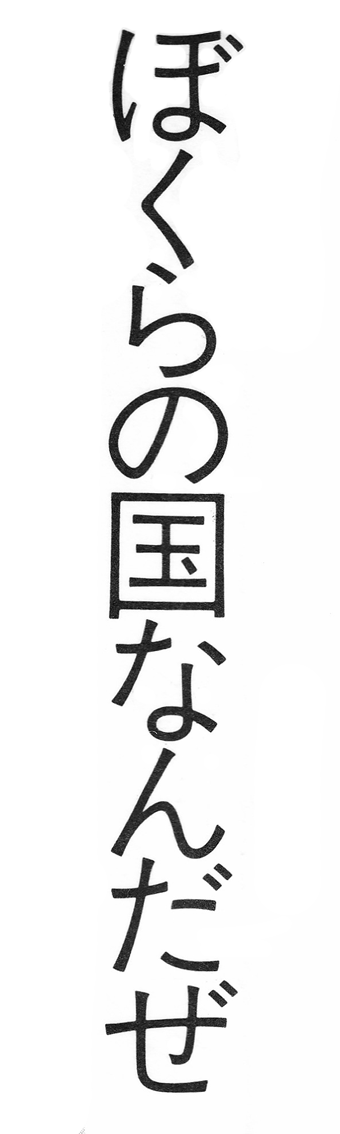
ポケットの なかには ビスケットが ひとつ
ポケットを たたくと ビスケットは ふたつ
もひとつ たたくと ビスケットは みっつ
たたいてみるたび ビスケットは ふえる
そんな ふしぎな ポケットが ほしい
(まどみちお『ふしぎなポケット』)
〈石井中ゴシック〉はあの歌に似ている。
いったいどこが似ているのか、どうしてそんなふうに感じるのか、わざわざ考えてみたことがなかったが、この書体の名前を知る以前からはっきりとそう思っていたし、だから私にとっては、比喩でもなんでもなく、ほんとうに「ビスケットの文字」だった。
高級というわけじゃないけれど、心惹かれる洒落たパッケージ、きっちりと整列している堅実な様。よけいな甘みをくわえていない、保存食みたいなビスケット。
もしも私に絶対音感があったなら、それを音楽で証明してみせるだろう、と考えることがある。
雨だれの音や、ごはん茶碗を並べる音でオーケストラをやってのける名指揮者のように、文字から伝わってくるイメージをうつくしい音にして、みんなに聴かせてあげられるのに、と。
でも残念ながら、私にはそんな音楽的才能はない。鼻歌をうたうのも、音楽をきくのも好きだけど、とにかく習い事全般を疎かにする子どもだったので、五年も習ったピアノは結局、バイエルさえものにならなかった(どうでもいいことだが、ピアノ教室へ行く途中の野原でへびいちごを摘むのが唯一の楽しみだったのを思いだした。田舎だなあ。)
だから私にできるのは、歌を口ずさみながらポケットをたたくことくらいだ。
これがリズムというものだと、いちばん最初に教えられた記憶。
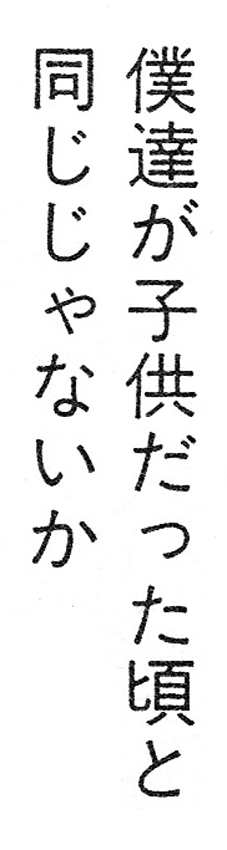
ポケットをたたくたびにビスケットの数が増えるのは、ポケットのなかでビスケットが割れるからだ、と人に聞いたことがある。
(この解釈には諸説あるようだけれど)そのとき私は、へえなるほど、といたく感心し、そういう意味で、この歌はやっぱり〈石井中ゴシック〉に似ていると思った。
この文字でかかれた言葉が目に入ってくるときの感覚は、ビスケットの歯ごたえにそっくりだ。ビスケットが割れる一瞬にくわわる力の、弱くもなく、強くもない、ほんのちょっと、手先に意識が集中する感じ。
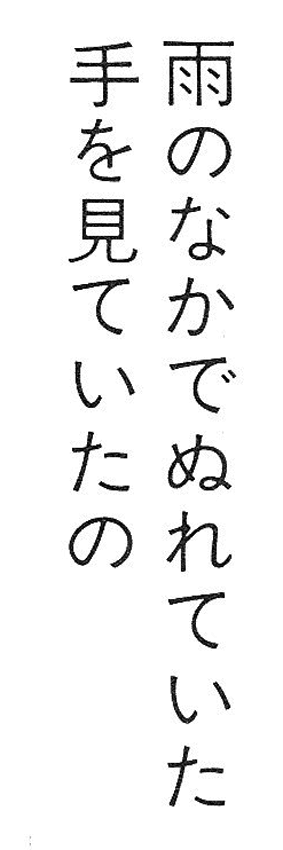
〈石井中ゴシック〉には、だから散文がよく似合う。
中学や高校のころ聴いていたCDの歌詞カードが〈石井中ゴシック〉でかかれているのをみると思わずぐっときてしまうのも、おそらく同じ気分によるものだろう。
それで思いあたることは他にもあって、たとえば、高野文子の「絶対安全剃刀」に収められている「うしろあたま」という作品。淡々とした小気味いいモノローグを読んでいると、どこにも音は鳴っていないのに、いつの間にか歌詞のようにみえてきて、音楽を聴いているみたいにうっとりしてしまう。
それは個人的な思い入れじゃないかといわれてしまうかもしれないし、事実その通りなのだが、どんなにポピュラーだと思われていることだって、実際はきわめて個人的な記憶の集合体であると思う。
私は(そんなことをしたら洗濯のとき怒られるのがわかっているので)ポケットのなかに本物のビスケットを入れた試しはないけれど、それでも、「ポケットのなかにビスケットがひとつ」の状態を確かに知っている、と思えたり、それはきっと自分だけじゃない、と信じられるのは、言葉の意味がひとつなのではなく、たぶんリズムの力なのだ。
長く愛されてきた書体にも、普遍的なリズムがある。身を委ねれば心躍る。
言葉を奏でるたびに、ひとつずつ、記憶の断片がふえていく。